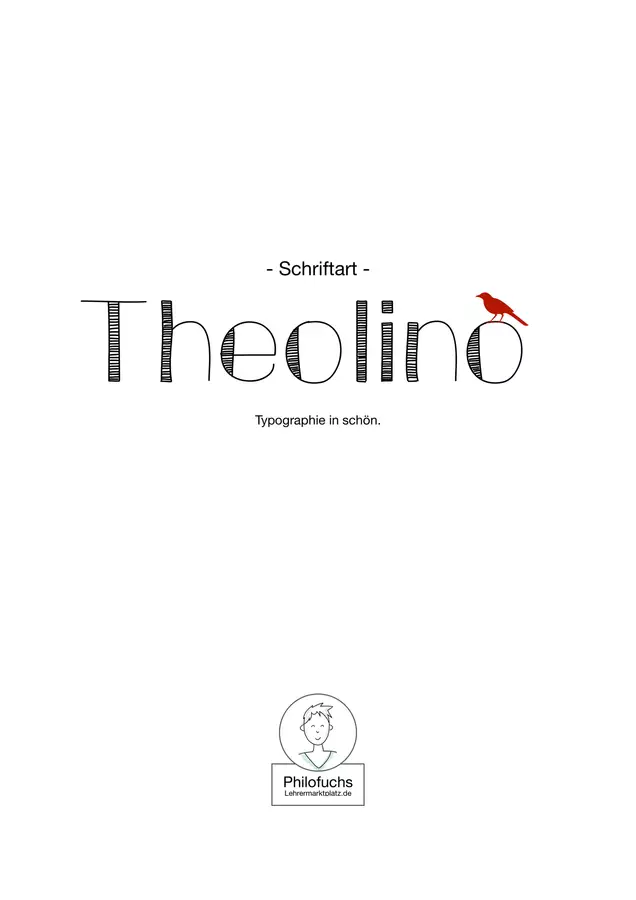
Stilvolles Layouten in schön. Durch einen Hauch „Handschrift“ lassen sich mit Theolino wunderbar typographische Akzente setzen, die Lehr- und Lernmaterial lebendig aufwerten. Dabei überzeugt Theolino auch in Kombination mit anderen Schriftarten (Arial, Helvetica, Georgia etc.) und trägt so zum individuellen Charakter der gestalteten Materialien bei.